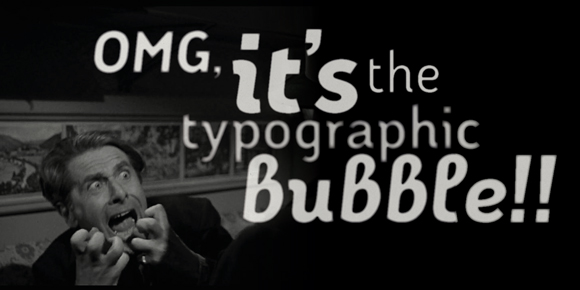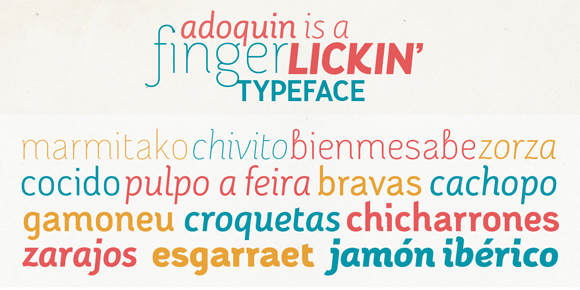
Juanjez López es un diseñador de raza que no da puntadas sin hilo. Hace ya algún tiempo nos presento «Adoquín» un palo seco de lineas bien definidas y distinguidas con algunos toques caligráficos que la hacian muy sabrosona. Pero a su ya notable cantidad de variables de peso, versalitas, ligaduras, etc le faltaba algo. Hoy nos presenta una compañera de baile perfecta, que cierra el círculo de esta versátil tipografía: nada más y nada menos que unas estupendas cursivas.
Ya no os queda ninguna excusa para no utilizar esta tipografía. Tenéis de todo, con la calidad y el gracejo que aporta a todo lo que hace este singular tipoduro.